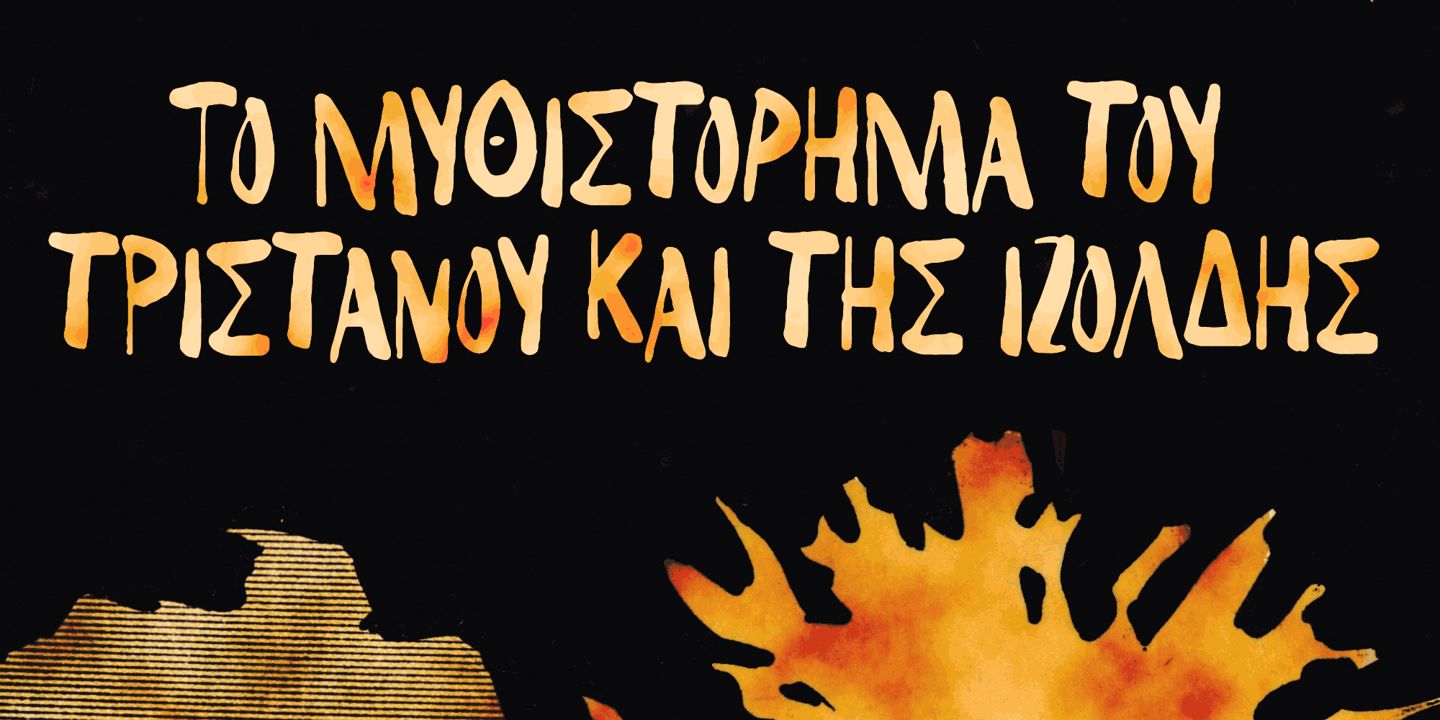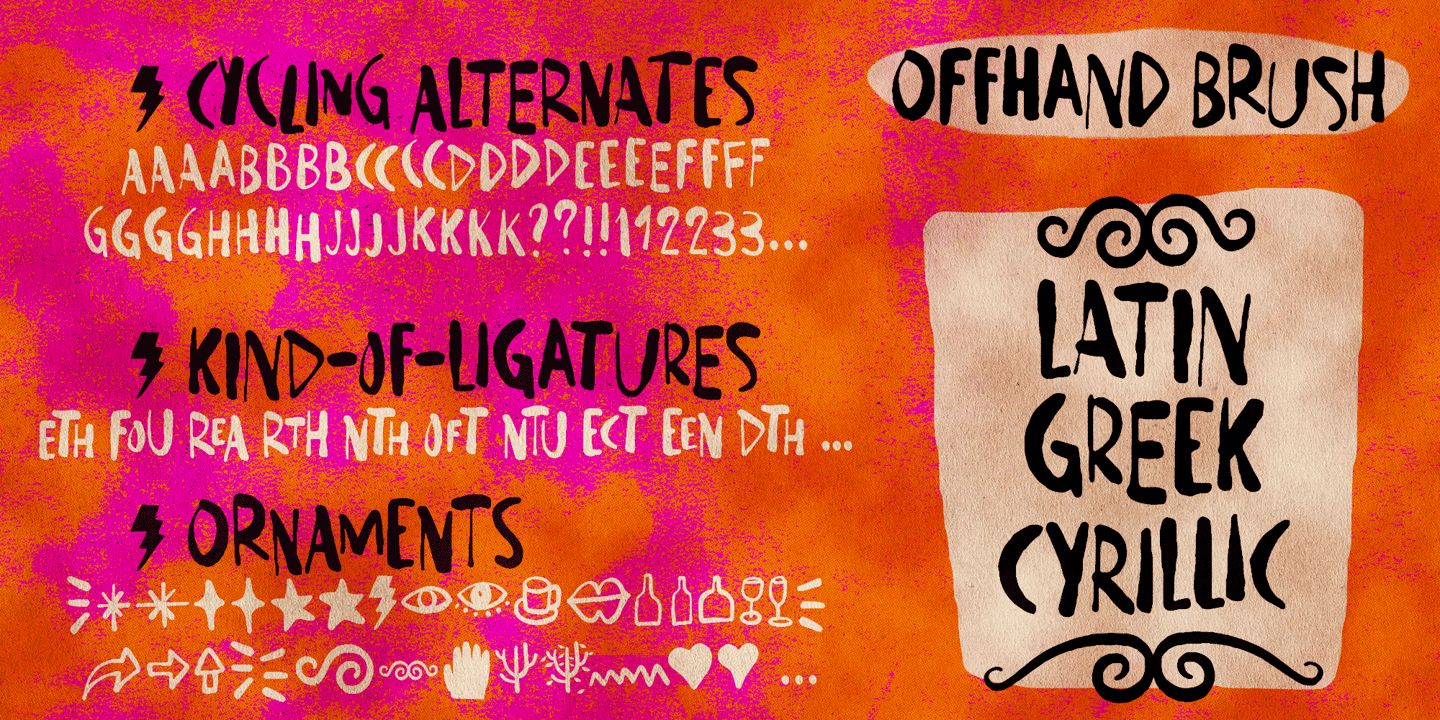
Offhand Brush Font
Description de Offhand Brush Font
Offhand Brush est une police de pinceau rapide et spontanée avec une sensation assez désordonnée, une excellente option pour les couvertures de livres, les projets d’emballage, les pochettes d’album, les titres Web et même de petits morceaux de texte. Cela semble compliqué, mais ne vous méprenez pas : à l’intérieur, c’est un travail laborieux, avec quatre alternatives pour chaque lettre latine et deux pour les chiffres, ainsi que deux options pour les lettres cyrilliques et grecques.
Pour rendre les choses encore plus inégales, il existe encore quelques modèles de lettres différents programmés pour apparaître lorsque des combinaisons spécifiques de trois ou quatre glyphes apparaissent dans le texte. Celles-ci sont gérées par la fonctionnalité « Ligatures standard » d’OpenType, bien qu’elles soient loin d’être standard et ne soient pas tout à fait des ligatures. Et pourquoi ? Parce que de cette façon, elle sera généralement activée par défaut, ce qui rendra la police beaucoup plus intéressante.